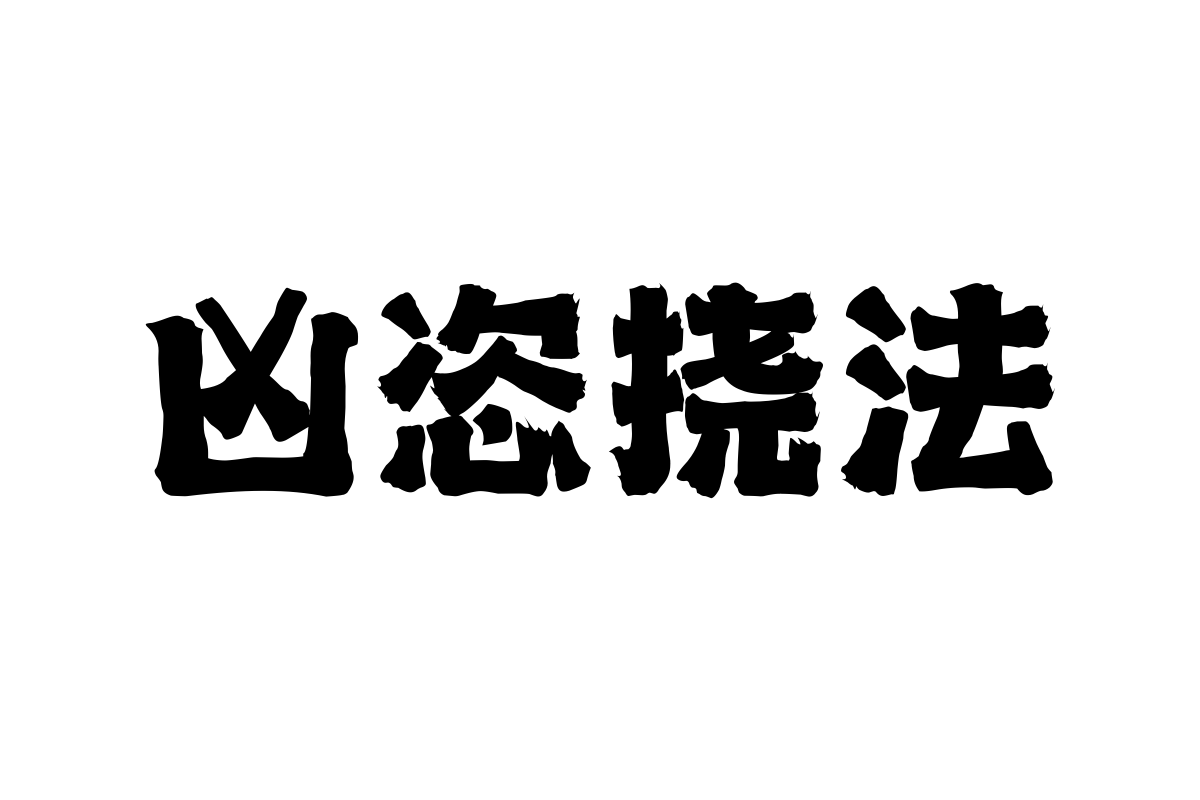
上首荒原体是一种手写字体,由日本书法家上首大介(Osamu Nagao)于1970年代设计。这种字体以其独特的笔触和结构而闻名,给人一种原始、自然的感觉。
上首荒原体的特点是其笔画粗细不一,线条流畅且具有动感。它的每个字母都呈现出一种独特的风格,使得整体看起来非常独特和引人注目。此外,这种字体还具有很高的辨识度,使其在广告、标识和其他视觉传达领域得到了广泛应用。
总的来说,上首荒原体是一种非常有特色的手写字体,它以其独特的笔触和结构赢得了广泛的喜爱和认可。